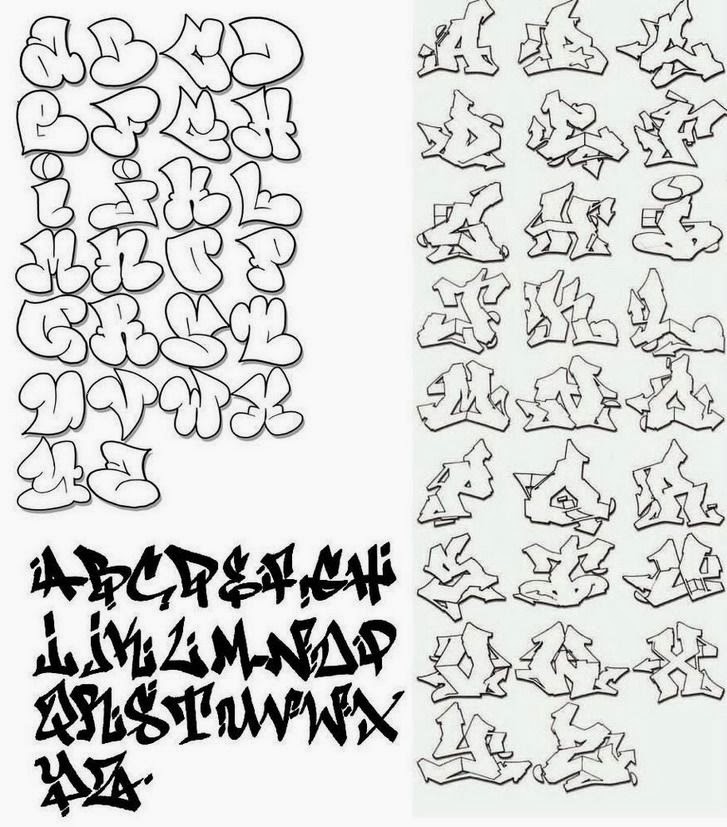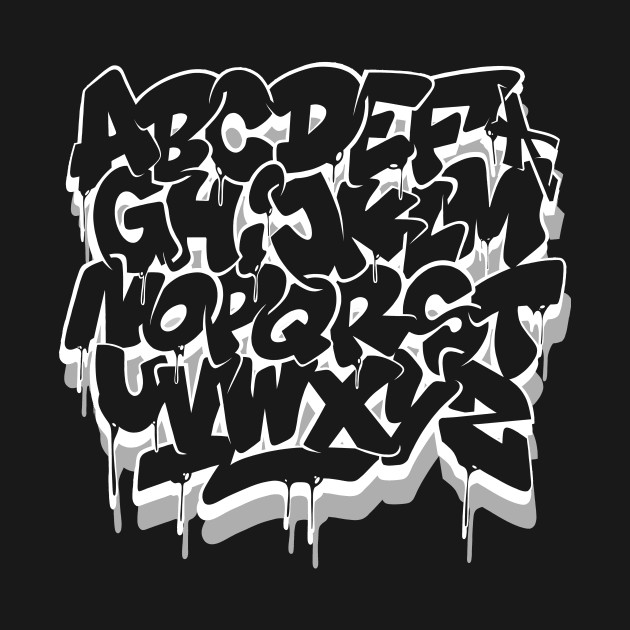
Супер шрифт для создания надписей в стиле Граффити. Поддерживает кириллицу и латиницу.
Граффити русские шрифты для иллюстратора. Семь кириллических шрифтов граффити
Многие райтеры имеют свой стиль и придумывают самостоятельно . Но все равно существуют основные принципы и шрифты, которыми пользуется большинство.
Я тоже иногда придумываю свои буквы и зарисовываю их на бумаге, во-первых, чтобы не забыть, а во вторых, воспроизводить на стене знакомый шрифт потом легче, чем изобретать что-то на ходу.
Самые распространенные стили написания и буквы граффити
Баббл
Такие мультяшные объемные буквы – самый распространенный вариант. В шрифте баббл буквы должны сливаться и как бы наплывать друг на друга. Единственный минус – иногда прочитать, что написано в этом стиле довольно трудно, так как буквы могут искажаться практически до неузнаваемости.
Блокбастерс
Для этого стиля граффити нужно сначала нанести на поверхность тон. Лучше сделать это при помощи валика, но можно и баллоном. Это работа не для одного и лучше выполнять ее вместе с товарищами. На фон наносятся ровные и четкие буквы граффити. Многие райтеры используют блокбастерс как свой фирменный стиль.
Вайлд
В этом стиле буквы граффити практически невозможно прочитать. Здесь можно проявить фантазию по полной программе. Буквы можно путать, дополнять их любыми элементами и сплетать самым невообразимым образом. Вайлд – довольно сложный авторский шрифт.
FX
Объемный граффити стиль и довольно сложный. Буквы в данном случае требуют тщательной проработки. Не советую новичкам пытаться начинать с него. Все равно ничего дельного не получится.
Мессия
Эти граффити буквы придумали в Америке. Многослойный шрифт с эффектом наложения изображений. Тоже не самый легкий вариант, который используют довольно опытные райтеры. Такие буквы граффити не нарисуешь за 15 минут.
Характер
Это уже даже не буквы, а целая картина. Нарисовать ее можно только при наличии разных насадок. Обычно в характере изображают героев комиксов.
Throw up
About Graffiti Fonts
Graffiti is usually appeared as graphics or lettering scratched, scrawled, painted or marked in any manner on property.
Graffiti has existed since very ancient times in Ancient Greece and the Roman Empire. In ancient Rome, people don’t have a photocopier or a fax machine or newspaper, and when you have a written message to let other people know, you scratched it on a wall. In modern times, however, graffiti is considered illegal in a lot of countries. But a country that with significant tradition in graffiti is Brazil and Sao Paulo, one of the largest cities in Brazil, is considered to be the current center of inspiration for graffiti artists.
Image courtesy of sfinbudapest.com
Graffiti can have different styles. Tagging is the simplest type of graffiti, usually done quickly in spray paint, markers or pens and lacking artistic form; A throw-up involves more work than tagging, usually having two or three colors and done in bubble letters; Stenciling can be a quick way to produce more complicated graffiti designs and by using two or more layers, you can produce color-rich designs; Wildstyle is a form of graffiti that was made popular by graffiti artists like Tracy 168, Zephyr in NYC.
Graffiti in Wildstyle is relatively more complicated and artistic. There are other forms of styles such as blockbuster, hip-hop, heaven, stickers, wheat pasting, etc. So there are a lot of styles of graffiti, hence, graffiti fonts.
Depending on your preferences, there are many fonts that can be used for graffiti purposes such as bubble fonts, stencil fonts , outline fonts etc. However, for complicated graffiti styles, they can never be achieved by fonts. Graffiti fonts can be a good way to study graffiti letters or graffiti alphabet, but you really should learn to express in your style. Get inspired and check out our collection of free graffiti fonts , or use our graffiti text generator below.
Create text-based logos or images with Graffiti Fonts
Below is a collection of graffiti fonts. The following tool will convert your desired text into images using graffiti fonts. Simply enter your text, select your desired color and size, and hit GENERATE button.
You can save your image by right-clicking on the image, or get codes to embed your images on the web by clicking on the EMBED button.
SELECT A FONT
Gretoon
gretoonhighlight
Adrenaline Zero
adrip1
Aerosol
cancontrol
dopejam
frankfrt
Friday13 Bonus NFI
maitai
markeraregular
mawns-graffiti-filled
mawnsrock1
metah
milky-well
misbhvn
MobileFont
redhead
RESKAGRAF
retaliat
rof
roosthea
roteflora
rotund
rotundo
ROUGD___
roughage
royalp
ruthlessdrippinone
ruthlessdrippintwo
ruthlesswreckinone
ruthlesswreckintwo
sailingjunco
tagsx
tagsxtreme
throwupz
08 Underground
aaaiight
aaaiight-fat
Abuse
Alphabet Black
Alphabet City
amsterdam
Antifont
Barrio Santo
BOMBFONT TRIAL
Bombing
BOREDSB
Brock Vandalo
CAKE!___
ChaseZenJackulator
CryOneDUC-Plain
degrassi back
degrassi front
degrassi
DJGROSS
docallismeonstreet
dumbnerd
Freight Train Gangsta
freshmarker
FreshTrack
From Street Art
GANG BANG CRIME
GasMaskWarriors
Ghetto Master
Ghetto Streetz
Graffiti font
Graffiti
Graffogie
graffonti.
3d.drop.
graffonti.atomic.bomb.
graffonti.gradient.fill.
JUICE___
Jungle LIFE
JUSTFIST
JUSTFIST2
KGRAFTRIAL
Kolossal black
Kolossal
kshandwrt
KZGRAVITY
LaksOner
LoSnello
Mad Bubbles
MAELS___
MagikMarker
Mainstream_PERSONAL_USE_ONLY
MARE 007
MARSNEVENEKSK
MAWNS Graffiti Filled
Mestizos Unidos — URBAN HOOKUPZ
mexican-pride-by-aspekhndz
MonstaTag_PersonalUse
Mostwasted
N!CE_Tag
Next Ups Black
Next Ups
No_License_Ghang
No_License_Ghang_Plain
NOSED___
PaintCans_09_FREE
Painterz
Patinio Graffiti
Peinture Fraiche
PhillySans
planet benson 2
PWGraffiti
RapScript_09
RapScript_Fade_09
RUFA
RuthlessDrippin1
RuthlessDrippin2
RuthlessWreckin1
RuthlessWreckin2
Sadoc Wild
Searfont
Sick Sketchlings
Sister Spray
Smasher 312 Black
Smasher 312 Custom
Smasher 312
SOUPER3
Sprayerz
Street Style
Street Writers
STYLEWARS 2011
Stylin BRK
subway
sweetasrevenge
TAGSTER
TheBattleCont
Throw-up Font
Tobec___
TURNB___
TURNBB__
Urban Calligraphy
urban decay
Urban Riot
URBAN_HOOK-UPZ
UrbRapper
Westcoast Ink
Whatka!
whoa!
WildBasic_free
writers_bold
writers_condensed
writers_original
None Gradient-Red-H Gradient-Green-H Gradient-Blue-H Gradient-Orange-H Gradient-Yellow-H Gradient-Purple-H Gradient-White-H Gradient-Black-H Gradient-Gold-H Gradient-Pink-H Gradient-Teal-H Gradient-Silver-H Gradient-Red-V Gradient-Green-V Gradient-Blue-V Gradient-Orange-V Gradient-Yellow-V Gradient-Purple-V Gradient-White-V Gradient-Black-V Gradient-Gold-V Gradient-Pink-V Gradient-Teal-V Gradient-Silver-V Gradient-Red-R Gradient-Green-R Gradient-Blue-R Gradient-Orange-R Gradient-Yellow-R Gradient-Purple-R Gradient-White-R Gradient-Black-R Gradient-Gold-R Gradient-Pink-R Gradient-Teal-R Gradient-Silver-R Shadow-Red-S Shadow-Green-S Shadow-Blue-S Shadow-Orange-S Shadow-Yellow-S Shadow-Purple-S Shadow-White-S Shadow-Black-S Shadow-Gold-S Shadow-Pink-S Shadow-Teal-S Shadow-Silver-S Shadow-Red-L Shadow-Green-L Shadow-Blue-L Shadow-Orange-L Shadow-Yellow-L Shadow-Purple-L Shadow-White-L Shadow-Black-L Shadow-Gold-L Shadow-Pink-L Shadow-Teal-L Shadow-Silver-L Outline-A Outline-B Outline-Transparent Style-Apple Style-Argentina Style-Backwoods Style-Baseball Style-BevelG Style-BevelS Style-Birthday Style-BlocksA Style-BlocksB Style-BoxLogo Style-BTTF Style-Chocolate Style-Chevron Style-Columbia Style-Comic Style-ConcaveB Style-ConcaveBB Style-ConcaveT Style-ConcaveTT Style-Condense Style-Cuphead Style-DragonB Style-Elegance Style-Frozen Style-GeoDash Style-Germany Style-GlitchA Style-GlitchB Style-Hexadots Style-Indiana-Jones Style-Ireland Style-Italy Style-KeepCalm Style-KISS Style-Mango Style-Mario Style-Milky Style-Mirrored Style-NameTag-Red Style-NameTag-Blue Style-Neon Style-NeonOutline Style-ObliqueR Style-OutlineGB Style-OutlineYB Style-OutlineUltra Style-Party Style-PAWP Style-Pokemon Style-PolkaDot Style-Popstar Style-Pressed Style-Rainbow Style-RobT Style-Romania Style-Russia Style-Sensual Style-Sesame Style-Slant Style-SmashB Style-Spain Style-Sports Style-StackedLines Style-Stamp Style-StarStripes Style-StarW Style-Steel Style-StickyNotes-A Style-StickyNotes-B Style-StickyNotes-C Style-StickyNotes-D Style-StraightOutta Style-ToyStory Style-Twitch Style-Twitter Style-Undertale Style-UPUP Style-Wood Style-Wavy Texture-Army Texture-Beer Texture-Bricks Texture-Cloth Texture-Cloud Texture-Chocolate Texture-Diamond Texture-Electric Texture-Fire Texture-Graffiti Texture-Granite Texture-Grid Texture-Hex Texture-Hot-Lava Texture-Iceberg Texture-Jigsaw Texture-Leaves Texture-Luxury Texture-Marble Texture-Metal Texture-Mirror Texture-Money Texture-Mud Texture-Paper Texture-Pool Texture-Rust Texture-Sky Texture-Slate Texture-Smog Texture-Space Texture-Steel Texture-Stripes Texture-Tiger Texture-Valentine Texture-Walnut Texture-Warning Texture-Water-Blue Texture-Water-Pink Texture-Waves Texture-Wheat Texture-Wood-A Texture-Wood-B Texture-Wood-C Texture-Wood-D Texture-Wood-E Texture-Wood-F
Шрифт граффити онлайн русские.
Многие райтеры имеют свой стиль и придумывают самостоятельно . Но все равно существуют основные принципы и шрифты, которыми пользуется большинство.
Я тоже иногда придумываю свои буквы и зарисовываю их на бумаге, во-первых, чтобы не забыть, а во вторых, воспроизводить на стене знакомый шрифт потом легче, чем изобретать что-то на ходу.
Самые распространенные стили написания и буквы граффити
Баббл
Такие мультяшные объемные буквы – самый распространенный вариант. В шрифте баббл буквы должны сливаться и как бы наплывать друг на друга. Единственный минус – иногда прочитать, что написано в этом стиле довольно трудно, так как буквы могут искажаться практически до неузнаваемости.
Блокбастерс
Для этого стиля граффити нужно сначала нанести на поверхность тон. Лучше сделать это при помощи валика, но можно и баллоном. Это работа не для одного и лучше выполнять ее вместе с товарищами.
На фон наносятся ровные и четкие буквы граффити. Многие райтеры используют блокбастерс как свой фирменный стиль.
Вайлд
В этом стиле буквы граффити практически невозможно прочитать. Здесь можно проявить фантазию по полной программе. Буквы можно путать, дополнять их любыми элементами и сплетать самым невообразимым образом. Вайлд – довольно сложный авторский шрифт.
FX
Объемный граффити стиль и довольно сложный. Буквы в данном случае требуют тщательной проработки. Не советую новичкам пытаться начинать с него. Все равно ничего дельного не получится.
Мессия
Эти граффити буквы придумали в Америке. Многослойный шрифт с эффектом наложения изображений. Тоже не самый легкий вариант, который используют довольно опытные райтеры. Такие буквы граффити не нарисуешь за 15 минут.
Характер
Это уже даже не буквы, а целая картина. Нарисовать ее можно только при наличии разных насадок. Обычно в характере изображают героев комиксов.
Throw up
А если вам нужно будет напечатать, например, книгу или какую-то брошюру, то тоже надо будет подобрать стиль, красивые буквы, заказать дизайн. Сейчас можно заказать даже совсем маленький тираж. Отличная печать, быстро выполняют заказ. Все подробности можно прочитать на сайте и там же заказать.
About Graffiti Fonts
Graffiti is usually appeared as graphics or lettering scratched, scrawled, painted or marked in any manner on property. Graffiti has existed since very ancient times in Ancient Greece and the Roman Empire. In ancient Rome, people don’t have a photocopier or a fax machine or newspaper, and when you have a written message to let other people know, you scratched it on a wall. In modern times, however, graffiti is considered illegal in a lot of countries. But a country that with significant tradition in graffiti is Brazil and Sao Paulo, one of the largest cities in Brazil, is considered to be the current center of inspiration for graffiti artists.
Image courtesy of sfinbudapest.com
Graffiti can have different styles. Tagging is the simplest type of graffiti, usually done quickly in spray paint, markers or pens and lacking artistic form; A throw-up involves more work than tagging, usually having two or three colors and done in bubble letters; Stenciling can be a quick way to produce more complicated graffiti designs and by using two or more layers, you can produce color-rich designs; Wildstyle is a form of graffiti that was made popular by graffiti artists like Tracy 168, Zephyr in NYC. Graffiti in Wildstyle is relatively more complicated and artistic. There are other forms of styles such as blockbuster, hip-hop, heaven, stickers, wheat pasting, etc. So there are a lot of styles of graffiti, hence, graffiti fonts.
Depending on your preferences, there are many fonts that can be used for graffiti purposes such as bubble fonts, stencil fonts , outline fonts etc. However, for complicated graffiti styles, they can never be achieved by fonts.
Graffiti fonts can be a good way to study graffiti letters or graffiti alphabet, but you really should learn to express in your style. Get inspired and check out our collection of free graffiti fonts , or use our graffiti text generator below.
Create text-based logos or images with Graffiti Fonts
Below is a collection of graffiti fonts. The following tool will convert your desired text into images using graffiti fonts. Simply enter your text, select your desired color and size, and hit GENERATE button. You can save your image by right-clicking on the image, or get codes to embed your images on the web by clicking on the EMBED button.
SELECT A FONT
Gretoon
gretoonhighlight
Adrenaline Zero
adrip1
Aerosol
cancontrol
dopejam
frankfrt
Friday13 Bonus NFI
maitai
markeraregular
mawns-graffiti-filled
mawnsrock1
metah
milky-well
misbhvn
MobileFont
redhead
RESKAGRAF
retaliat
rof
roosthea
roteflora
rotund
rotundo
ROUGD___
roughage
royalp
ruthlessdrippinone
ruthlessdrippintwo
ruthlesswreckinone
ruthlesswreckintwo
sailingjunco
tagsx
tagsxtreme
throwupz
08 Underground
aaaiight
aaaiight-fat
Abuse
Alphabet Black
Alphabet City
amsterdam
Antifont
Barrio Santo
BOMBFONT TRIAL
Bombing
BOREDSB
Brock Vandalo
CAKE!___
ChaseZenJackulator
CryOneDUC-Plain
degrassi back
degrassi front
degrassi
DJGROSS
docallismeonstreet
dumbnerd
Freight Train Gangsta
freshmarker
FreshTrack
From Street Art
GANG BANG CRIME
GasMaskWarriors
Ghetto Master
Ghetto Streetz
Graffiti font
Graffiti
Graffogie
graffonti.
3d.drop.
graffonti.atomic.bomb.
graffonti.gradient.fill.
JUICE___
Jungle LIFE
JUSTFIST
JUSTFIST2
KGRAFTRIAL
Kolossal black
Kolossal
kshandwrt
KZGRAVITY
LaksOner
LoSnello
Mad Bubbles
MAELS___
MagikMarker
Mainstream_PERSONAL_USE_ONLY
MARE 007
MARSNEVENEKSK
MAWNS Graffiti Filled
Mestizos Unidos — URBAN HOOKUPZ
mexican-pride-by-aspekhndz
MonstaTag_PersonalUse
Mostwasted
N!CE_Tag
Next Ups Black
Next Ups
No_License_Ghang
No_License_Ghang_Plain
NOSED___
PaintCans_09_FREE
Painterz
Patinio Graffiti
Peinture Fraiche
PhillySans
planet benson 2
PWGraffiti
RapScript_09
RapScript_Fade_09
RUFA
RuthlessDrippin1
RuthlessDrippin2
RuthlessWreckin1
RuthlessWreckin2
Sadoc Wild
Searfont
Sick Sketchlings
Sister Spray
Smasher 312 Black
Smasher 312 Custom
Smasher 312
SOUPER3
Sprayerz
Street Style
Street Writers
STYLEWARS 2011
Stylin BRK
subway
sweetasrevenge
TAGSTER
TheBattleCont
Throw-up Font
Tobec___
TURNB___
TURNBB__
Urban Calligraphy
urban decay
Urban Riot
URBAN_HOOK-UPZ
UrbRapper
Westcoast Ink
Whatka!
whoa!
WildBasic_free
writers_bold
writers_condensed
writers_original
None Gradient-Red-H Gradient-Green-H Gradient-Blue-H Gradient-Orange-H Gradient-Yellow-H Gradient-Purple-H Gradient-White-H Gradient-Black-H Gradient-Gold-H Gradient-Pink-H Gradient-Teal-H Gradient-Silver-H Gradient-Red-V Gradient-Green-V Gradient-Blue-V Gradient-Orange-V Gradient-Yellow-V Gradient-Purple-V Gradient-White-V Gradient-Black-V Gradient-Gold-V Gradient-Pink-V Gradient-Teal-V Gradient-Silver-V Gradient-Red-R Gradient-Green-R Gradient-Blue-R Gradient-Orange-R Gradient-Yellow-R Gradient-Purple-R Gradient-White-R Gradient-Black-R Gradient-Gold-R Gradient-Pink-R Gradient-Teal-R Gradient-Silver-R Shadow-Red-S Shadow-Green-S Shadow-Blue-S Shadow-Orange-S Shadow-Yellow-S Shadow-Purple-S Shadow-White-S Shadow-Black-S Shadow-Gold-S Shadow-Pink-S Shadow-Teal-S Shadow-Silver-S Shadow-Red-L Shadow-Green-L Shadow-Blue-L Shadow-Orange-L Shadow-Yellow-L Shadow-Purple-L Shadow-White-L Shadow-Black-L Shadow-Gold-L Shadow-Pink-L Shadow-Teal-L Shadow-Silver-L Outline-A Outline-B Outline-Transparent Style-Apple Style-Argentina Style-Backwoods Style-Baseball Style-BevelG Style-BevelS Style-Birthday Style-BlocksA Style-BlocksB Style-BoxLogo Style-BTTF Style-Chocolate Style-Chevron Style-Columbia Style-Comic Style-ConcaveB Style-ConcaveBB Style-ConcaveT Style-ConcaveTT Style-Condense Style-Cuphead Style-DragonB Style-Elegance Style-Frozen Style-GeoDash Style-Germany Style-GlitchA Style-GlitchB Style-Hexadots Style-Indiana-Jones Style-Ireland Style-Italy Style-KeepCalm Style-KISS Style-Mango Style-Mario Style-Milky Style-Mirrored Style-NameTag-Red Style-NameTag-Blue Style-Neon Style-NeonOutline Style-ObliqueR Style-OutlineGB Style-OutlineYB Style-OutlineUltra Style-Party Style-PAWP Style-Pokemon Style-PolkaDot Style-Popstar Style-Pressed Style-Rainbow Style-RobT Style-Romania Style-Russia Style-Sensual Style-Sesame Style-Slant Style-SmashB Style-Spain Style-Sports Style-StackedLines Style-Stamp Style-StarStripes Style-StarW Style-Steel Style-StickyNotes-A Style-StickyNotes-B Style-StickyNotes-C Style-StickyNotes-D Style-StraightOutta Style-ToyStory Style-Twitch Style-Twitter Style-Undertale Style-UPUP Style-Wood Style-Wavy Texture-Army Texture-Beer Texture-Bricks Texture-Cloth Texture-Cloud Texture-Chocolate Texture-Diamond Texture-Electric Texture-Fire Texture-Graffiti Texture-Granite Texture-Grid Texture-Hex Texture-Hot-Lava Texture-Iceberg Texture-Jigsaw Texture-Leaves Texture-Luxury Texture-Marble Texture-Metal Texture-Mirror Texture-Money Texture-Mud Texture-Paper Texture-Pool Texture-Rust Texture-Sky Texture-Slate Texture-Smog Texture-Space Texture-Steel Texture-Stripes Texture-Tiger Texture-Valentine Texture-Walnut Texture-Warning Texture-Water-Blue Texture-Water-Pink Texture-Waves Texture-Wheat Texture-Wood-A Texture-Wood-B Texture-Wood-C Texture-Wood-D Texture-Wood-E Texture-Wood-F
Помощь сайту
Понравился сайт? Уроки оказались полезными? Вы можете поддержать проект, просто если скачаете и установите приложение «Фонарик» для Андроид.
Приложение написал автор сайта и рассчитывает в дальнейшем публиковать свои приложения. Фонарик управляет светодиодом вспышки фотокамеры телефона, а также включает подсветку экраном на полной яркости.
Преимущества: гибкие настройки. Вы можете задать в настройках, чтобы фонарик сразу включался при запуске приложения и автоматическое включение таймера при запуске приложения. Настройки позволяют отключить блокировку экрана и блокировку фонарика кнопкой включения телефона. Также вы можете самостоятельно установить время таймера.
Если приложение наберёт популярность, это даст стимул автору на создание новых приложений с учётом пожеланий посетителей сайта.
Заранее благодарен, Дмитрий.
QR-код для установки:
Если Вам понравился материал, скажите свое «спасибо», поделитесь ссылками с друзьями в социальных сетях! Спасибо!
Огромные граффити украсили фасады домов в Челябинской области | Pchela.news
Новости
Новые муралы появились в Снежинске и посёлке Локомотивный.
Так, в закрытом городе уличные художники нарисовали на стене жилого дома гигантского снегиря, а в Локомотивном фасад школы украсило изображение велосипедиста. Об этом сообщили в пресс-службе Главного управления молодёжной политики Челябинской области.В Снежинске на улице Васильева художник из Перми Висмут Тляшев изобразил снегиря в стиле оригами.
Молодой человек рисует на стенах уже более 15 лет. Он начинал с классических граффити-шрифтов, постепенно добавляя к ним персонажей. Сейчас основным направлением его творчества является реализм, который иногда дополняется элементами графики, оригами и граффити.
— Я пока не вкладываю в свои работы каких-то глубоких смыслов, — подчеркнул автор. — Пусть каждый интерпретирует работу так, как он видит.
А в посёлке Локомотивный на здании местной школы по улице Мира появилось изображение велосипедиста.
Граффити нарисовал художник Евгений Ганг.
Молодой южноуралец — профессиональный художник и татуировщик, работающий в разных стилях и техниках.
— Моя работа — это манифест, призывающий взрослых отвлечься от бесконечной суеты повседневной жизни, остановиться и обратить внимание на новое поколение, понять его, — прокомментировал Евгений Ганг. — Мы не должны забывать о времени, когда сами были детьми, проще относились к миру, никуда не торопились и с лёгкостью принимали перемены.
В рамках фестиваля «Наш Mural» в разных городах Челябинской области художники рисуют гигантские граффити. Кроме того, в это время работают арт-резиденции, участникам которых рассказывают о разных направлениях современного искусства, читают лекции.
Ранее в Челябинске преобразили фасад здания волейбольного клуба «Динамо-Метар». На граффити изобразили выпускниц клуба, известных российских волейболисток — Евгению Старцеву и Екатерину Гамову, отбивающих метеоритный мяч.
Фото: предоставлены пресс-службой Управления молодёжной политики Челябинской области
Подписывайтесь в Telegram
Больше новостей
Автор: Айдар Насыров
Поделиться
—>
Автор: Айдар Насыров
Поделиться
—>
Автор: Ирина Горностаева, Айдар Насыров
Поделиться
—>
Автор: Ирина Горностаева, Айдар Насыров
Поделиться
—>
Автор: Ирина Горностаева, Айдар Насыров
Поделиться
—>
Автор: Ирина Горностаева, Айдар Насыров
Поделиться
—>
Автор: Айдар Насыров
Поделиться
—>
Автор: Айдар Насыров
Поделиться
—>
Автор: Айдар Насыров
Поделиться
—>
Автор: Айдар Насыров
Поделиться
—>
Автор: Айдар Насыров
Поделиться
—>
Автор: Ирина Горностаева, Айдар Насыров
Поделиться
—>
Автор: Челябинский зоопарк/Vk.
com
Поделиться
—>
Автор: Айдар Насыров
Поделиться
—>
Автор: Ирина Горностаева, Айдар Насыров
Поделиться
—>
Автор: Айдар Насыров
Поделиться
—>
Автор: Айдар Насыров
Поделиться
—>
Автор: Мария Минина
Поделиться
—>
Автор: Наталья Фомина
Поделиться
—>
Автор: общественная организация «АнтиСмог»
Поделиться
—>
Автор: Айдар Насыров
Поделиться
—>
Автор: Ирина Горностаева, Айдар Насыров
Поделиться
—>
Автор: Айдар Насыров, Борис Абрамов, Дмитрий Абрахин
Поделиться
—>
Автор: Никита Лисовский, Айдар Насыров
Поделиться
—>
Автор: Айдар Насыров
Поделиться
—>
Автор: Ирина Горностаева, Айдар Насыров
Поделиться
—>
Автор: ФКУ Упрдор «Южный Урал»
Поделиться
—>
Автор: Айдар Насыров
Поделиться
—>
Автор: Айдар Насыров
Поделиться
—>
Автор: Ирина Горностаева, Айдар Насыров
Поделиться
—>
Автор: Ирина Горностаева, Айдар Насыров
Поделиться
—>
Автор: Ирина Горностаева, Айдар Насыров
Поделиться
—>
Автор: Ирина Горностаева, Айдар Насыров
Поделиться
—>
Автор: Ирина Горностаева, Айдар Насыров
Поделиться
—>
Автор: Ирина Горностаева, Айдар Насыров
Поделиться
—>
Автор: Ирина Горностаева, Айдар Насыров
Поделиться
—>
Автор: Ирина Горностаева, Айдар Насыров
Поделиться
—>
Автор: Айдар Насыров
Поделиться
—>
Автор: Айдар Насыров
Поделиться
—>
Автор: Ирина Горностаева, Айдар Насыров
Поделиться
—>
Автор: Ирина Горностаева, Айдар Насыров
Поделиться
—>
Автор: Ирина Горностаева, Айдар Насыров
Поделиться
—>
Автор: Айдар Насыров
Поделиться
—>
Автор: Ирина Горностаева, Айдар Насыров
Поделиться
—>
Автор: Айдар Насыров
Поделиться
—>
Автор: Айдар Насыров
Поделиться
—>
Автор: Айдар Насыров
Поделиться
—>
Автор: группа «Я выхожу Челябинск»/Telegram
Поделиться
—>
Автор: Айдар Насыров
Поделиться
—>
Автор: Ирина Горностаева, Айдар Насыров
Поделиться
—>
Автор: Ирина Горностаева, Айдар Насыров
Поделиться
—>
Автор: Ирина Горностаева, Айдар Насыров
Поделиться
—>
Автор: Ирина Горностаева, Айдар Насыров
Поделиться
—>
Автор: Никита Лисовский
Поделиться
—>
Автор: Ирина Горностаева, Айдар Насыров
Поделиться
—>
Автор: Ирина Горностаева, Айдар Насыров
Поделиться
—>
Автор: Ирина Горностаева, Айдар Насыров
Поделиться
—>
Автор: Айдар Насыров
Поделиться
—>
Автор: Ирина Горностаева, Айдар Насыров
Поделиться
—>
Автор: Никита Лисовский
Поделиться
—>
Автор: Ирина Горностаева, Айдар Насыров
Поделиться
Лента новостей
Все новости
что нужно знать о художнике – DW – 15.
08.2022Фото: Hannibal Hanschke/dpa/picture-alliance
КультураГермания
Елена Дожина
15 августа 2022 г.
Замечательный художник Дмитрий Врубель родился в СССР, а в 2010 году уехал из России в Берлин. 14 августа он умер в Германии. Ему было всего лишь 62 года. Каким мы его запомним?
https://www.dw.com/ru/dmitri-wrubel-glawnoe-o-nem/a-62814489
Реклама
«Братский поцелуй», просто «Поцелуй» и даже «Поцелуй смерти», — это варианты названия одной и той же картины-граффити Дмитрия Врубеля, которую он написал прямо на Берлинской стене. Фрагмент Стены стал основой художественной галереи под открытым небом East Side Gallery в берлинском районе Фридрихсхайн. И картина российского художника здесь — чуть ли не главный артефакт. На провокационном шедевре Врубеля запечатлен страстный поцелуй генсека ЦК КПСС Леонида Брежнева и лидера ГДР Эриха Хонеккера (Erich Ernst Paul Honecker).
Первый вариант граффити художник создал в 1990 году и подписал на русском и немецком: «Mein Gott, hilf mir, diese tödliche Liebe zu überleben» или «Господи! Помоги мне выжить среди этой смертной любви!». Из СССР пригласили пятерых художников — для того, чтобы сделать первую в ГДР выставку современного советского искусства. До падения Берлинской стены граффити на ней были только со стороны Запада. Врубель стал одним из первопроходцев с Востока.
«Сюжет» позаимствован с фотоснимка корреспондентки газеты Frankfurter Allgemeine Барбары Клемм (Barbara Klemm), сделанном на праздновании 30-летия ГДР. За 10 лет до падения Берлинской стены тогдашние генсек ЦК КПСС Леонид Брежнев и генсек ЦК СЕПГ Эрик Хонеккер закрепили братскую любовь между СССР и ГДР долгим и крепким поцелуем. Граффити советского художника стало в итоге одним из символов падения Берлинской стены.
Исторический сюжетФото: Spiegl/SVEN SIMON/SvenSimonНовый вариантФото: Ingo Schulz/ImageBroker/picture alliance Первый вариант «Поцелуя»Фото: DB Kathrin Brunnhofer/dpa/picture-allianceВ 2009 году во время реставрации части Стены, известной сегодня как East Side Gallery, одна из самых ярких картин была удалена.
Разгорелась нешуточная дискуссия о том, восстанавливать ее или нет. Большинство художников не хотели рисовать свои картины заново, опасаясь, что галерея превратится в подобие «Диснейленда» для туристов, а также того, что выделенные на восстановление средства утекут в чужой карман. Однако Дмитрий Врубель снова прибыл в Берлин и за пару недель воссоздал «Братский поцелуй». Сегодня он — на своем старом месте, в черте города. И именно эта культовая картина №25 на Берлинской стене является, пожалуй, самым популярным в немецкой столице фотомотивом — разве что после Бранденбургских ворот и рейхстага.
Врубель — это про «взорвать мозг»
В 2010 году Дмитрий Врубель с супругой, художницей Викторией Тимофеевой, и сыном переехал из России в Германию. В последнее время они разрабатывали выставки с использованием технологий виртуальной реальности и в 2018 году открыли свой 3D-проект для доступа широкой публике — чтобы люди в городах, где нет Лувра или Эрмитажа, тоже могли приобщиться к искусству.
«Быть в Берлине и выставлять свои работы в России в виртуальной реальности — это потрясающее ощущение», — признался Дмитрий Врубель в одном из интервью DW. У художника всегда получалось идти в ногу со временем и использовать новые технологии, потому что «современный художник должен быть современным во всем».
С помощью специальных компьютерных программ творческий тандем Врубеля и Тимофеевой создал выставочные пространства и «развесил» в них картины. Отсутствие цензуры, возможность демонстрировать искусство с политическим подтекстом и широкая доступность 3D-выставок — главные причины, побудившие художников трансформировать свои работы в виртуальную реальность. Экспозиция доступна на платформе Steam. С помощью очков виртуальной реальности можно увидеть около 100 монументальных полотен в натуральную величину: проект «Толстоевский», «Евангельский проект», «Дневник художника», а также реконструкция квартирной выставки советских времен.
Экскурсию «проводит» аватар Дмитрия Врубеля — шустрый парень в футболке, скачущий от картины к картине и эмоционально размахивающий руками. В планах Дмитрия Врубеля было создание «Музея события», который должен был освещать и осмыслять важные новости с позиций искусства.
Художник мечтал о превращении в самое большое арт-пространство в мире… Лубянки! «Самая первая большая выставка современного русского искусства должна быть на Лубянке — как в зданиях «штази». Лубянка должна стать самым большим арт-сквотом в мире. Но сначала нужно вывезти все эти документы «рейхсканцелярии» на архивирование», — съязвил Дмитрий Врубель в интервью DW.
Как российский художник стал немецким пиратом
Чтобы быть ближе к проблемам рядовых немцев, вскоре после переезда в Берлин Врубель вступил в «Партию пиратов». «Пираты» выступали за легализацию «пиратства» в интернете, мягкую наркополитику, введение избирательного права для всех жителей Германии (вне зависимости от гражданства) и так далее.
«Они мне близки по духу, так как хотят активно менять общество и решать проблемы, о которых традиционные партии не в состоянии думать в силу своего консервативного мышления», — прокомментировал тогда свое решение Врубель.
Своим «коньком» художник считал интеграцию Берлина посредством культурной интервенции. «Там, где стоит East Side Gallery, раньше был пустырь. После того, как художники разрисовали стену, Берлин в этом месте начал срастаться. Сейчас это модный район», — рассказывал Врубель. «То, что люди в так называемых проблемных зонах не интересуются современным искусством, есть проблема современного искусства», — считал он. Искусство отдалилось от людей, и поэтому художник стремился свести их снова вместе — как в фильме Вернера Херцога (Werner Herzog) «Фицкарральдо» (Fitzcarraldo), в котором эксцентричный авантюрист, которого играет Клаус Кински (Klaus Kinski), хочет построить в джунглях оперный театр. Но Врубель был настроен серьезно, при этом — без гнева и тщеславия.
Мечтатель-интеллигент из диссидентской среды
Дмитрий Врубель родился в 1960 году в Москве в семье инженеров, рисовать начал в подростковом возрасте. В 20 лет вступил в Союз художников, а через несколько лет уже открыл собственную галерею, назвав ее своим именем. В 1970-80-х он, как и многие коллеги-художники, которых сегодня называют концептуальными художниками, организовывал выставки у себя на квартире или в своей мастерской. В то время он создавал в основном крупноформатные портреты. Свой, пожалуй, самый провокационный шедевр на Берлинской стене художник написал в 30 лет.
«Я хотел бы жить в Москве так, как я живу в Берлине. Берлин — это идеальная Москва. Но при нынешней власти в России очень сложно заниматься политическим искусством. А искусство вне политического контекста мне неинтересно», — признавался художник.
С 2010 года Врубель постоянно проживал с супругой в Берлине, где они создали открытую мастерскую. У художника было множество персональных и групповых выставок по всему миру.
Его работы представлены в известнейших музеях. Берлин стал для Врубеля второй родиной, а «Братский поцелуй» прославил рожденного в СССР художника на весь мир. Многие из тех, кто фотографируется сегодня на фоне шедевра Врубеля, может даже и не знать, кто эти люди на фрагменте Стены и почему вообще целуются генсеки. И вряд ли юные туристы станут запоминать невеселые подробности социалистической дружбы, зато не забудут короткое имя: Врубель.
Смотрите также:
Врубель и Тимофеева: мы нарисуем конец путинизма
To view this video please enable JavaScript, and consider upgrading to a web browser that supports HTML5 video
Написать в редакцию
Реклама
Пропустить раздел Топ-тема1 стр. из 3
Пропустить раздел Другие публикации DWНа главную страницу
Смоляне могут выбрать эскиз граффити для здания общежития смоленского драмтеатра
Культура 365
Поделиться
Департамент Смоленской области по внутренней политике по поручению Губернатора Смоленской области Алексея Владимировича Островского проводит голосование среди жителей города Смоленска по выбору эскиза тематического граффити для здания общежития смоленского драмтеатра.
Отдать свой можно на платформе «Общественного голосования» портала Госуслуг по ссылке.
Выбрать можно один из трех вариантов:
1. Музы покровительницы театра — Талия и Мельпомена, олицетворяющие комедию и трагедию.
2. Концепция на тему прошлого и будущего. Лицо разделено на две части, отражающие разные эпохи.
3. Концепция на тему произведения М. Булгакова «Мастер и Маргарита».
Голосование продлится до 14 сентября 2022 года.
Спешите отдать свой голос за понравившийся эскиз!
Подписаться
Смоленск
- 30 авг
Престиж и пополнение бюджета: названы плюсы коротких автомобильных номеров
- 22 авг
Штраф за невыгул: назван способ перевоспитания российских собаководов
- 16 авг
Названо лучшее средство от пробок на дорогах России
Что еще почитать
Индастри-пленэр: в Смоленске показали результаты работы художников на заводе КДМ
Фото 407
Мария Ледовская
СмоленскАвтор детских книг рассказала о непростом пути к творчеству
Фото 1166
Мария Ледовская
СмоленскPeople: учительницу средней школы арестовали за изнасилование
13332
Олег Цыганов
Киев заявил о ракетном ударе в Кривом Роге, разлился Ингулец
24285
Эмма Грибова
Эксперт объяснил, как в Ставропольском крае оказался беспилотник
41493
Зиля Гумерова
Что почитать:Ещё материалы
В регионах
Аксенов ответил Киеву на фейки об эвакуации: «эвакуаторы хреновы»
17194
КрымФото: управление информации и пресс-службы Главы Республики Крым
Самые вкусные оладьи из кабачков по-новому
12168
КалугаЕлена Одинцова
Полиция задержала 50 девушек в красном на петрозаводской площади Кирова.
ФОТОФото 11148
КарелияИрина Стафеева
За час до рассвета: пропавший на трассе в Челябинской области дальнобойщик покончил с собой
Фото 5277
ЧелябинскИрина Меньшикова
Как получить звание ветерана труда
2733
Великий НовгородБелобородько Мария
«Надо настраиваться»: стилист в Улан-Удэ предсказала возвращение моды нулевых годов
Фото 2335
Улан-УдэСэсэг Жигжитова
В регионах:Ещё материалы
Download 806 Graffiti Fonts — Envato Elements
Download 806 Graffiti Fonts — Envato ElementsRefine by
Refine by
Related:
- procreate
- brush
- gangsta
- neon
- music font
Сортировать по RelevantPopularNew
Graffiti Line — Display Graffiti Font
By shanafart in Шрифты
Добавить в коллекцию
Nightfate Graffiti — FOLD GRAFFITI FONT
BY FIGEE IN FONTS
Добавить в коллекцию
Streamzy — Graffiti Font
BOZART — Шрифт Graffiti
By tokopress in Шрифты
Добавить в коллекцию
Districtside — Tagged Graffiti
от Invasistudio в шрифтах
Добавить в коллекцию
Arcinoll — граффити -шрифт
от Alterzone in Fonts
Add to Collection
- 9008 GUSTAVAVE Add в коллекцию
- 9008 GUSTAVAVEAVE999999999999999.
Добавить в коллекцию
Luser Graffiti Bold
By Holismjd in Fonts
Добавить в коллекцию
Warxer Graffiti Font
By maulanacreative in Fonts
Add to collection
Download
The Overcook — Graffiti Font
By arendxstudio in Fonts
Add to collection
Download
Hayword – a Graffiti Style
By garisman in Fonts
Добавить в коллекцию
Download
MostWanted Graffiti Font
By yipianesia in Fonts
Добавить в коллекцию
Бескджек — Граффити -шрифт
от GraphicFresh в шрифтах
Add в коллекцию
Losdol — Graffiti Font
Skatenow | Граффити Шрифт
By Vunira in Шрифты
Добавить в коллекцию
Getrok — Граффити Шрифт
по приоритетному точке. Шрифты
Добавить в коллекцию
Shadowgraff — Graffiti Font
By STRstudio in Шрифты
Добавить в коллекцию
Download
Kliwon Street Graffiti Font
By zerologicstudio in Fonts
Add to collection
Download
INSANITY — Graffiti font
By Tokokoo in Fonts
Add to collection
Download
Hollowtown – Рукописное граффити
By typefactoryco in Шрифты
Добавить в коллекцию
Wonder Gangs Graffiti Font
от TypeCoConut In Fonts
Add to Collection
Toughart — граффити -шрифт
от Tokomoo в Fonts
Add to Collection
Добавить в коллекцию
Rhieknuza — Graffiti Font
By StringLabs in Fonts
Добавить в коллекцию
Слепота граффити — городской шрифт
от Colllabstudio в шрифтах
Добавить в коллекцию
Bold Street — Граффити.
Грязнобольной | Шрифт Graffiti Logotype
Автор: dirtylinestudio in Шрифты
Добавить в коллекцию
KINGER — Graffiti Display Font
от Twinletter in Fonts
Добавить в коллекцию
Nossible — простой граффити -шрифт
от Gassstype в шрифтах
add в коллекцию
Загрузка
9000GRAFFIT.
Tagged Vol.1By nomores в Шрифты
Добавить в коллекцию
New Kids Crew — Graffiti Type
Автор ikiikowrk в Шрифты
Добавить в коллекцию
Загрузить
Роллер | Фонд граффити
от Vunira in Fonts
Add to Collection
Bombero — Graffiti Font
By Blugalds in Fonts
Add в Collection
9009 9009Add в Collection
- 9009
Add Collection
- 9009
Add For
9009 9009.
in FontsДобавить в коллекцию
Download
Southsider — Graffiti Typeface
By Blankids in Fonts
Добавить в коллекцию
Bombsky Graffiti Font
By Blankids in Fonts
Добавить в коллекцию
Shocker Tide -Grab
Bembies — Graffiti Font
By Blankids in Fonts
Добавить в коллекцию
Offstoke Graffiti Font
от MaulanAcreative в шрифтах
Добавить в коллекцию
Babayaro — Graffiti Font
By Tokopress в Fonts
Add Collection
9000.
Добавить в коллекцию
Shockwave — Graffiti Font
By Tokokoo in Fonts
Добавить в коллекцию
Макстильд | Граффити шрифт
от Garisman in Fonts
Добавить в коллекцию
Darksite — Городский граффити -шриф in Fonts
Добавить в коллекцию
Download
Lodstay — Graffiti Font
By Blankids in Fonts
Add to collection
Download
Related:
- procreate
- brush
- gangsta
- neon
- music font
12345
17 pages
Related searches from other categories
Дополнения
кисти для граффити3d brushbrickstrokebrush
Музыка
thug lifedubstep ambientpaintercool introcuba
Получите 7 дней неограниченного количества загрузок бесплатно.
Начать 7-дневную бесплатную пробную версию
50 лучших граффити-шрифтов для вашего городского дизайна
Vandelay Design может получать компенсацию от компаний, продуктов и услуг, представленных на нашем сайте. Для получения более подробной информации, пожалуйста, обратитесь к нашей странице раскрытия информации.
У нас есть то, что вам нужно, если вы графический дизайнер и хотите добавить немного уличного стиля в свои городские проекты. Ознакомьтесь с нашей свежей и классной коллекцией граффити-шрифтов.
Что такое граффити-шрифты? По сути, это декоративные шрифты, имитирующие внешний вид уличного искусства. Вдохновленные граффити, они могут выглядеть как аэрозольная краска, каракули или трафареты и часто включают капли краски, эффекты гранжа и брызги для завершения внешнего вида. Их можно использовать в различных дизайнерских проектах, от логотипов и брендинга до упаковки и одежды.
Граффити уходит своими корнями в вандализм, но со временем оно стало уважаемым видом искусства.
Чаще всего это можно увидеть в городских районах и городских районах, поэтому имеет смысл использовать шрифты граффити в дизайне, который требует эстетики уличного искусства.
Когда дело доходит до использования граффити-шрифтов, следует помнить о нескольких вещах. Во-первых, из-за того, что они настолько богато украшены, их может быть трудно читать, особенно в небольших размерах. Поэтому лучше не использовать их для основного текста или других текстовых элементов. Затем соедините граффити-шрифты с простыми шрифтами без засечек для максимальной контрастности и удобочитаемости.
НЕОГРАНИЧЕННАЯ ЗАГРУЗКА: более 50 миллионов шрифтов и элементов дизайна
Лучшие шрифты для граффити
Художники граффити имеют уникальный взгляд на мир, и их искусство часто отражает это. Граффити-шрифты не являются исключением и могут придать вашему дизайну городской оттенок. Вот 50 лучших шрифтов для граффити, которые помогут начать ваш следующий дизайн-проект.
Если вы любите шрифты, вам определенно стоит попробовать Envato Elements. Подписавшись на Elements, вы получите неограниченных загрузок 25 000 шрифтов , а также миллионов других ресурсов , таких как темы WordPress, стоковые фотографии, графика, звуковые эффекты и многое другое. Это лучшая ценность, которую вы можете найти в индустрии дизайна.
Rollover
Первым идет Rollover, необычный шрифт, который выглядит как капающая краска. И, если вы сделаете шрифт темно-красным, он легко будет выглядеть как кровь, так что он может выполнять двойную функцию в качестве шрифта ужасов. Этот шрифт является хорошим выбором для макетов плакатов, обложек книг, дизайна одежды и многого другого.
Загружаемый zip-файл включает прописные и строчные буквы, цифры, знаки препинания, контекстные и стилистические варианты, лигатуры и многоязычную поддержку.
Losdol
Вот блочный шрифт граффити в мультяшном стиле, который идеально подходит для того, чтобы придать вашим проектам вид классического граффити, сохраняя при этом достаточно разборчивость для коммерческих проектов.
Попробуйте его для одежды, плакатов или логотипов.
Загрузка включает прописные и строчные буквы, цифры, знаки препинания, многоязычную поддержку и веб-шрифт.
Nightfate Graffiti
Nightfate — это большой, жирный и уникальный шрифт, вдохновленный хип-хопом, который добавит городскую атмосферу любому графическому дизайну, в котором вы его используете. Будь то логотип, брошюра, флаер, плакат, обложка книги, или графику в социальных сетях, этот шрифт с заглавными буквами выполнит свою работу.
ZIP-архив со шрифтами содержит прописные буквы, цифры, знаки препинания и веб-шрифт.
Звезда фанки
Это произведение понравится артистам! Funky Star наполнен стилистическими вариантами, поэтому вы можете создать уникальный типографский шедевр с буквами, которые характеризуют веселый и причудливый стиль граффити.
Загрузка включает прописные буквы, строчные буквы, цифры, знаки препинания, альтернативные наборы символов,
Trainidath
Trainidath выглядит как граффити старой школы с блочными, нарисованными от руки, перекрывающимися буквами и отражениями.
Он идеально подходит для широкого спектра проектов, таких как афиши мероприятий, обложки альбомов, цитаты, логотипы, брендинг и многое другое.
Загрузка включает прописные буквы, цифры, знаки препинания, многоязычные специальные символы и веб-шрифты.
Notress
Вот декоративный шрифт с аутентичным видом граффити. У него сложные формы букв и интересные формы, которые уникальны для этого стиля письма. Используйте Notress для городской одежды, дизайна логотипов, упаковки, настенного искусства и графики для социальных сетей.
Загрузка шрифта включает прописные буквы, цифры, знаки препинания и веб-шрифт.
Streamzy
Интересный взгляд на жанр! Streamzy сочетает стиль смелого шрифта граффити с игривым видом детского шрифта, что делает его идеальным выбором для дизайна видеоигр, плакатов детских мероприятий, флаеров, обложек детских книг и других беззаботных дизайнов.
Загрузка шрифта включает прописные и строчные буквы, цифры и знаки препинания.
Hayword
Вдохновленный уличным искусством, Hayword представляет собой шрифт в стиле граффити, напоминающий надписи на тегах. Попробуйте использовать этот декоративный шрифт для дизайна одежды, настенных цитат, постеров фильмов, графики в социальных сетях, заголовков веб-сайтов и обложек книг.
Этот архив со шрифтами включает прописные и строчные буквы, цифры, знаки препинания и многоязычную поддержку.
Районсайд
Вот еще один шрифт, который был вдохновлен тегами и выглядит так, как будто он был создан с помощью маркера. Он был создан, чтобы быть смелым, легко читаемым и идеально подходящим для того, чтобы добавить нотку уличного стиля в ваши проекты. Используйте его для редакционных макетов, графики для социальных сетей, упаковки продуктов, брендинга, логотипов и многого другого.
Загрузка включает символы верхнего регистра, цифры, знаки препинания, альтернативы, лигатуры, многоязычную поддержку и веб-шрифты.
Airneo
Airneo — это забавный граффити-шрифт с заглавными буквами и деталями в виде стрелок.
Строчные буквы тоже заглавные, но без стрелок. Существует также полный набор альтернативных глифов со стрелками, указывающими в противоположном направлении, поэтому вы можете начинать и заканчивать свою типографику со стрелками, указывающими так, как вы хотите.
Загрузка шрифта включает все заглавные буквы, цифры, знаки препинания, альтернативные варианты и многоязычную поддержку.
Бесстрашная королева
Бесстрашная королева — это брашированный шрифт с элементами граффити и ретро-эстетикой. Он идеально подходит для дизайна, связанного с музыкой, например флаеров концертов, плакатов, постов в социальных сетях и обложек альбомов. Но не ограничивайтесь только музыкальным дизайном — он также подходит для рекламы, цитат и брендинга.
Загрузка включает все прописные буквы, цифры, знаки препинания, лигатуры, многоязычную поддержку и веб-шрифты.
Darksite
Этот городской граффити-шрифт идеально подходит для дизайна упаковки, дизайна футболок, плакатов, графики для социальных сетей, логотипов и многого другого.
Darksite имеет классический вид граффити с тегами и включает в себя бонусный шрифт swash, чтобы придать вашим проектам еще большую достоверность.
Загрузка включает все прописные буквы, цифры, знаки препинания, многоязычную поддержку, веб-шрифт и бонусные росчерки.
Offstoke
Это шрифт среднего размера, монолинейный в стиле граффити, который добавит урбанистическую нотку вашим коммерческим и личным проектам. Используйте его для графики в социальных сетях, цитат, заголовков веб-сайтов и обложек видео на YouTube.
Загрузка включает прописные и строчные буквы, цифры и знаки препинания.
Luser Graffiti Bold
Вдохновленный современным уличным искусством и хип-хоп музыкой, Luser представляет собой смелый шрифт для граффити, отличающийся короткими игривыми буквами. У этого есть атмосфера граффити, но его довольно легко читать, поэтому используйте его для заголовков, редакционных макетов, листовок, плакатов, цитат и дизайна одежды.
Загрузка включает прописные буквы, цифры, знаки препинания и веб-шрифты.
Dripster
Вот шрифт для тегов граффити, который станет отличным дополнением к вашему дизайнерскому портфолио. Создатель Dripster воспользовался ссылками из различных граффити для создания этого классного шрифта, который обязательно добавит изюминку вашему дизайну, вдохновленному граффити, будь то логотип, бренд одежды, дизайн 80-х, цитата или флаер.
Загрузка шрифта включает заглавные буквы, цифры и знаки препинания.
Стены Техаса
Стены Техаса — это шрифт граффити с вольными характеристиками классического уличного искусства, такими как уникальные перекрывающиеся формы и капающая краска. Это отличный выбор для брендов городской одежды, обложек альбомов и вывесок.
Загрузка шрифта включает прописные буквы, цифры, знаки препинания, лигатуры, альтернативы, многоязычные акценты и веб-шрифт.
Lodstay
Lodstay — это еще одна форма граффити-шрифта в стиле уличных тегов с забавной атмосферой, что делает его хорошим выбором для всего: от комиксов до детских книг, флаеров с музыкой в стиле хип-хоп и обложек альбомов.
Попробуйте этот с дизайном одежды, упаковкой и логотипами.
Загрузка шрифта включает прописные и строчные буквы, цифры, знаки препинания и многоязычную поддержку.
Street Hipster
Если вы ищете нарисованный от руки шрифт в стиле граффити, который легко читается, но при этом имеет бунтарский резкий вид, вы его нашли! Street Hipster — отличный выбор для заголовков веб-сайтов, афиш мероприятий, обложек альбомов, графики для социальных сетей и вывесок.
Застежка-молния со шрифтом содержит прописные и строчные буквы, цифры, знаки препинания и многоязычную поддержку.
Bomber Squad
Bomber Squad — это трехмерный шрифт в забавном мультяшном стиле граффити. Он поставляется с версиями сплошного и теневого контура, которые вы можете комбинировать для создания трехмерного вида. Этот шрифт — отличный выбор для постеров, флаеров, комиксов, обложек книг и любых коммерческих проектов.
Загрузка включает все заглавные буквы, цифры, знаки препинания и многоязычную поддержку.
Arcinoll
Этот беззаботный и забавный шрифт представляет собой рукописный маркерный шрифт, вдохновленный уличным искусством и граффити. Это отличный выбор для цитат, рекламных листовок, одежды, плакатов, графики для социальных сетей и любых других проектов, требующих немного шика.
ZIP-файл включает все заглавные буквы, цифры, знаки препинания, лигатуры, многоязычную поддержку и веб-шрифт.
НЕОГРАНИЧЕННАЯ ЗАГРУЗКА: более 50 миллионов надстроек и ресурсов дизайна
The Ponkys
Если ваш дизайн требует яркого шрифта с жирным шрифтом, отличительными символами и стилями граффити, попробуйте The Ponkys . Этот уникальный шрифт с заглавными буквами имеет аутентичный уличный стиль, который может вывести ваш дизайн на новый уровень.
Загрузка шрифта включает все заглавные буквы, цифры, знаки препинания, росчерки и многоязычную поддержку.
Hokia
Hokia — еще один шрифт для тегов граффити, идеально подходящий для упаковки продуктов, брендинга, графики в социальных сетях, логотипов, цитат и других проектов, требующих острой и крутой городской эстетики.
ZIP-файл включает прописные и строчные буквы, цифры, знаки препинания и многоязычную поддержку.
The Bold Street
Этот шрифт в стиле граффити может быть вдохновлен уличным искусством, но его милые мультяшные персонажи-пузыри хорошо подходят для детских книг, комиксов и упаковки детских товаров. Конечно, это также хорошо сработает и для городских проектов.
Шрифт включает прописные и строчные буквы, цифры, знаки препинания, многоязычную поддержку и веб-шрифт.
Southsider
Используйте такой шрифт, как Southsider, чтобы добавить дополнительный характер и сделать ваши проекты по-настоящему яркими! Вдохновленный музыкой хип-хоп и стилем граффити, этот дисплейный шрифт имеет ярко выраженный уличный стиль, но сохраняет разборчивые буквы, что делает его отличным выбором для заголовков, редакционных макетов, листовок, плакатов и многого другого.
Загрузка включает прописные и строчные буквы, цифры и знаки препинания.
Throws
Если вы ищете аутентичные граффити-шрифты в стиле Throws, Throws — это то, что вам нужно! Stack Throws Fill и Throws Line для достижения внешнего вида.
Кернинг и интервалы плотные, как настоящие на улицах. Это не становится намного более реалистичным, чем это.
Загрузка шрифта включает два шрифта — Throws Fill и Throws Line, с прописными и строчными буквами, цифрами и пунктуацией.
Hidebeast
Hidebeast — это жирный и крупный нарисованный от руки шрифт, вдохновленный граффити, который представлен в двух стилях — контурном и блочном. Его громкое, веселое, мультяшное качество делает его хорошим выбором для упаковки энергетических напитков, комиксов, дизайна видеоигр, постов в социальных сетях, плакатов и всего остального, что требует веселого и прикольного шрифта с городским оттенком.
Загрузка включает оба шрифта с прописными и строчными буквами, числами, пунктуацией, многоязычной поддержкой и веб-шрифтами.
East Coast Wild Style
East Coast Wild Style — это рукописный шрифт для тегов, воплощающий уличный стиль. Он включает в себя бонусный набор штрихов, которые вы можете использовать для еще большей достоверности.
Этот шрифт трудно читать, и он должен быть таким, поэтому используйте его осторожно — для флаеров, обложек альбомов, дизайнов футболок и многого другого.
Почтовый индекс включает прописные буквы, строчные буквы, цифры, знаки препинания и росчерки.
Bembies
Вот однострочный маркерный шрифт от легкого до среднего, вдохновленный свободным и плавным стилем граффити. Bembies хорошо подойдут для дизайна в стиле хип-хоп, приглашений на вечеринки, листовок с мероприятиями, дизайна футболок, комиксов, графики для социальных сетей и настенного искусства.
Загрузка шрифта включает все заглавные буквы, цифры, знаки препинания и многоязычную поддержку.
RaseOne
Семейство шрифтов RaseOne представлено в пяти стилях — Fill, Fade, Color, Fat 3D и Outline, что дает вам множество вариантов дизайна. Сам шрифт довольно уникален, он немного похож на нечто среднее между шрифтом граффити и шрифтом в стиле татуировки. Вы также получаете множество специальных символов, таких как стрелки, завитки и начальные и конечные полосы для ваших букв.
Это воплощение мечты любителя типографики. Загрузка включает пять шрифтов с прописными и строчными буквами, цифрами и пунктуацией.
Street Explorer
Street Explorer вдохновлен граффити на городских улицах. Пухлые пузырчатые буквы характерны для стиля граффити, известного своими простыми формами, которые можно быстро «выбросить». Симпатичные круглые буквы будут хорошим выбором для любого дизайна, который требует граффити, но они также хорошо подойдут для детских проектов.
ZIP-файл содержит прописные и строчные буквы, цифры, знаки препинания, лигатуры, альтернативы и веб-шрифт.
Night Vandal
Используйте этот великолепный граффити-шрифт, чтобы вывести свой городской дизайн на новый уровень. Как следует из названия, Night Vandal был вдохновлен уличным искусством и действительно имеет вид классического граффити. Попробуйте этот для создания уникальных логотипов и монограмм или городского дизайна футболок.
Загрузка включает все заглавные буквы, цифры и знаки препинания.
Basketor
Если вы все еще ищете что-то необычное, как насчет этого монолинейного маркерного шрифта с изюминкой… эти буквы, вдохновленные уличным искусством, выглядят стильно! Они сочатся от дерзости! Basketor — отличный выбор для спортивных логотипов, винтажных дизайнов, брендинга, флаеров и плакатов.
Загрузка шрифта включает прописные и строчные буквы, цифры, знаки препинания и многоязычную поддержку.
Snikers
Вот шрифт граффити в стиле каллиграфического маркера, который вы можете использовать, чтобы легко включить стиль уличного искусства в свой дизайн. Созданный настоящим художником-граффити, Snikers — отличный выбор для рекламы, редакционных макетов, графики для социальных сетей, дизайна одежды и логотипов.
zip со шрифтами включает все заглавные буквы, цифры, знаки препинания, росчерки, многоязычную поддержку и веб-шрифты.
Rhieknuza
Rhieknuz — классный и причудливый шрифт, вдохновленный граффити, в котором есть все необходимое для придания урбанистического вида вашим проектам.
Более того, это вполне разборчиво, но при этом выглядит как стрит-арт. Это хороший выбор для дизайна одежды, цитат, макетов журналов, плакатов и многого другого.
Morfem